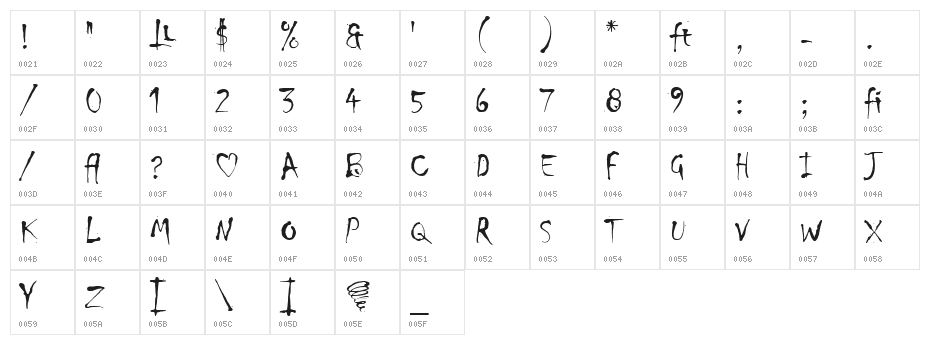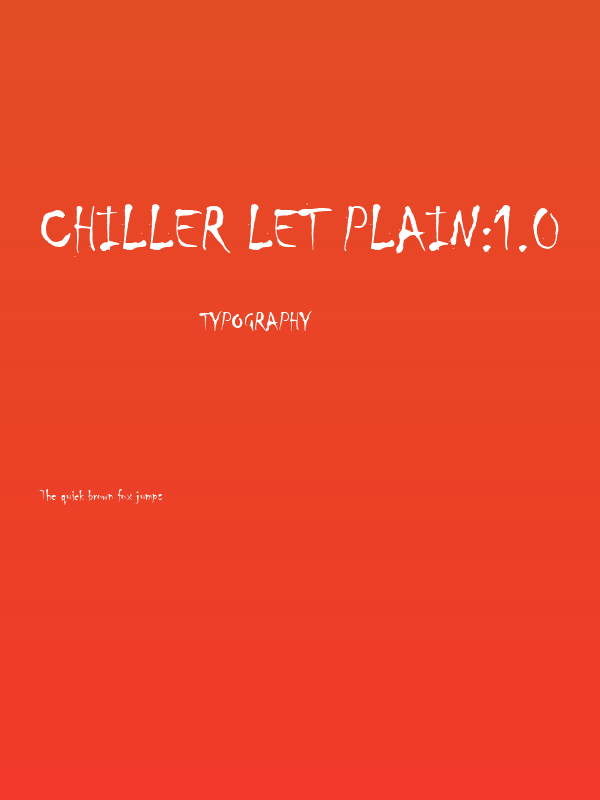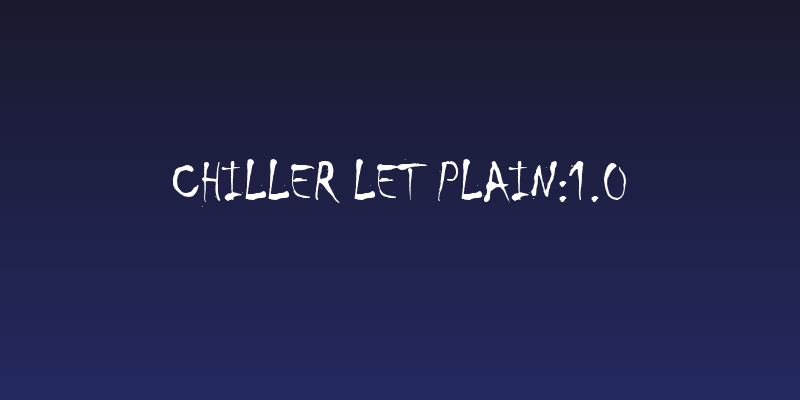
Chiller LET Plain:1.0 Font
| Caso d'uso | Headlines, Posters, Themed Events |
| Progetti proposti | Ideal for Halloween invitations, horror movie posters, themed party decorations, and spooky graphic designs. |